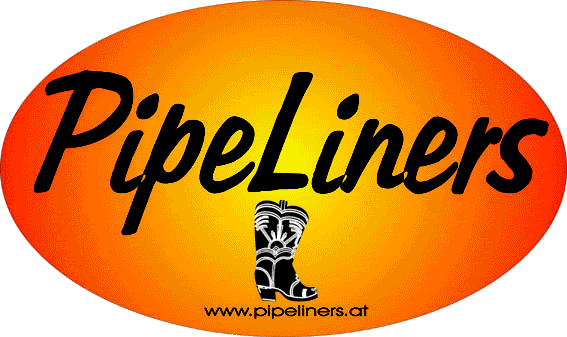
Nun hoffe ich, dass ihr mir bei der Suche nach der Schrift vom Logo weiterhelfen könnt.
Das Logo ist 2000 gemacht worden und den PC gibt es leider nicht mehr dazu.
Als ähnliche Schrift habe ich die Blacklight D gefunden, allerdings bin ich damit nicht ganz glücklich. Das i sieht doch anders aus und das P und das L sind kleiner und gedrungener.
Ich hoffe ihr könnt mir weiterhelfen, bin über jeden Tipp wie ich zu der Schrift komme dankbar.
Über die Homepage "WhatTheFont" bin ich auch schon gestolpert, allerdings funktioniert das mit dem Logo einlesen nicht so optimal.
Den Überscheidungen an den Strichen nach zu urteilen, muss das, wenn überhaupt, ein ganz bescheidener free-font sein. Sei froh, dass Du ihn nicht mehr findest und such Dir bei mfont o.ä. was neues aus.
Das mag sein. Allerdings werden T-Shirts und Hemden so bestickt bzw. bedruckt und unsere Gürtelschnalle und Bolotie wurden auch danach gefertigt, deswegen möchte ich die Schrift nicht wechseln.
Es muss auch nicht die Schrift von damals sein, aber sie sollte so nah wie möglich rankommen.
Gibt es Firmen die Schriften nach Wunsch "zeichnen" bzw. "nachbauen". Das wäre nämlich sonst noch eine gute Variante für mich.
Du kannst den Schriftzug in Illustrator doch auch ganz leicht selbst nachzeichen, bzw. abpausen.
Magst du mir erzählen was der Illustrator ist. Ich bin weder Grafikerin noch sonst wie mit diesen Dingen vorbelastet. Und was macht man mit den restlichen Buchstaben, die man nicht kennt.
Nachbauen ist sicher die beste Vorgehensweise, dabei kann man das auch gleich glätten (z. B. die unsauberen Überschneidungen corrigieren). Entweder Du entscheidest Dich für die lokale Variante und telephonierst mal ein paar Grazer Druckereien oder Agenturen ab, oder Du rufst hier noch mal vernehmlich um Hilfe, dann bekommst Du bestimmt ein paar PNs von unterbeschäftigten Collegen.
Die Schrift der Netzadresse ist übrigens eine arg gequetschte Avant Garde (falls das auch von Interesse ist). Die sollte bei einer Aufarbeitung auch mal in ihre Originalproportionen zurückversetzt werden.
Diesen Schriftzug in eine Vektorgrafik (das sind solche, bei denen eine Größenänderung ohne Qualitätsverlust möglich ist) zu verwandeln, ist eine Aufgabe, die jeder Grafikerdesigner/Mediengestalter/Gebrauchsgrafiker ohne Schwierigkeiten erledigen können sollte. Dabei könnten dann auch die häßlichen Überschneidungen beseitigt werden. Ich würde da zu einem lokalem Anbieter Deines Vertrauens raten, mit dem man u.U. weiter zusammen arbeiten könnte.
Natürlich gibt es auch Schriftgestalter, die Dir gern eine exklusive Hausschrift erstellen. Das ist aber wegen des erheblichen Aufwands nicht ganz billig. Bevor Du hier investierst, würde ich doch dazu raten, darüber nachzudenken, ob nicht doch eher ein neues Logo oder eine schön gestaltete Wortmarke trotz der eventuell nötigen neuen Geschäftsausstattung eine lohnende Investition wäre. Das ist oft weniger teuer als vermutet (eventuell läßt sich so etwas ja auch koordinieren: man führt das z.B. mit der nächsten nötigen T-Shirt-Bestellung ein). Denn das was Du uns hier zeigst, ist tatsächlich nicht besonders gut. Das wirkt sich schon auch darauf aus, wie man von möglichen Kunden wahrgenommen wird. Wer will schon unprofessionell wirken?
Wenn es doch im Do-it-Yourself-Verfahren passieren muss: mit Vektormagic erreiht man beim vektorisieren sehr akzeptable Ergebnisse. Ansonsten hilft die Faustregel: einfach halten. Ein einfacher, sauber gesetzter Schriftzug wäre wohl schon besser als das, was Du jetzt hast.
Die Buckles und Boloties sind gerade erst gemacht worden. Die Hemden können nicht alle neu gemacht werden, da ist der Aufwand einfach zu groß. Und auch der finanzielle Aufwand. Und T-Shirts kommen jetzt zwar wieder neue, aber die alten werden weiterhin im Gebrauch sein und das fände ich dann auch nicht so gut. Wir sind ein Verein und für das machen wir das eh schon relativ professionell. ;-)
Die Schrift der Netzadresse ist nicht so wichtig, da sie doch sehr klein ist und auch nicht so markant, könnte man die ändern, die ist auch nicht auf den Hemden und T-Shirts drauf.